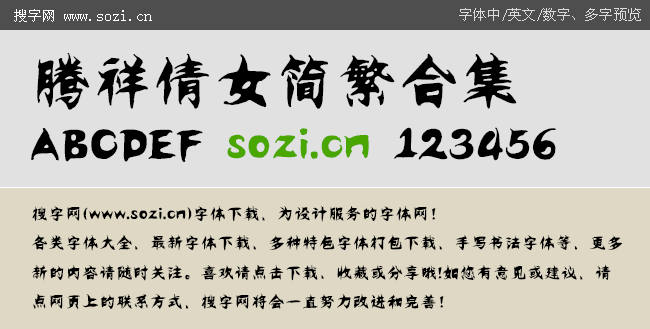
騰祥倩女簡(jiǎn)繁合集
搜字網(wǎng)提供一款騰祥倩女簡(jiǎn)繁合集中文藝術(shù)字體下載,騰祥倩女簡(jiǎn)繁合集是一款手寫風(fēng)格的書法字體,字體大方得體,效果非常漂亮,可以應(yīng)用于橫幅標(biāo)語、美術(shù)設(shè)計(jì)、宣傳海報(bào)、圖形設(shè)計(jì)等領(lǐng)域。